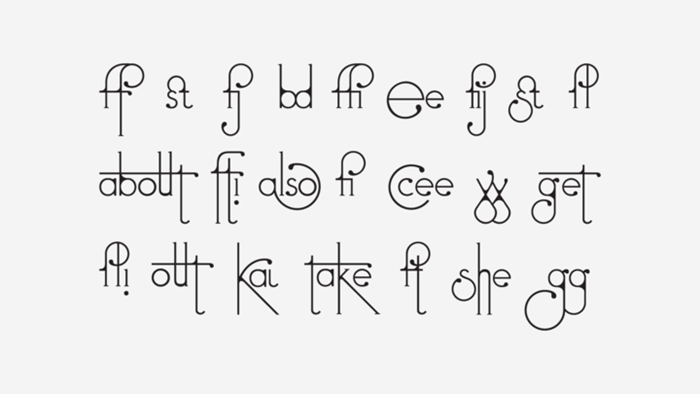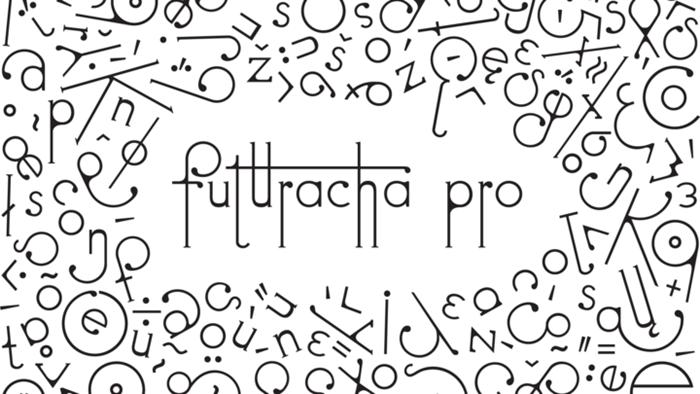
สร้างงานดีไซน์ให้ล้ำได้อีก!! ด้วยฟอนต์แปลงร่าง “Futuracha Pro” ที่ได้รับแรงบันดาลใจมาจากแมลงสาบ
เบื่อกับการใช้ฟอนต์ เรียบ ๆ เดิม ๆ กับงานออกแบบของคุณกันบ้างไหมครับ ? วันนี้ผมมีฟอนต์เจ๋ง ๆ มาแนะนำกัน รับรองว่าฟอนต์นี้จะทำให้ท่านต้องตะลึงเพราะว่ามันสามารถเปลี่ยนรูปร่างของตัวเองได้ตามการใช้งานของเรา ถ้าพร้อมแล้ว ไปรู้จักกับ ฟอนต์ “Futuracha Pro” กันเลยครับ
ความพิเศษของฟอนต์ Futuracha Pro นี้คือมันสามารถปรับและเปลี่ยนรูปแบบของตัวอักษรได้ด้วยตัวของมันเอง ซึ่งการเปลี่ยนรูปแบบของมันนั้น จะเปลี่ยนไปตามรูปแบบคำ รูปแบบประโยคที่คุณพิมพ์ครับ
โดยเจ้าฟอนต์ที่เปลี่ยนร่างได้เรื่อย ๆ นี้ เป็นผลงานการออกแบบโดยกราฟิกดีไซน์เนอร์นามว่า Odysseas Galinos Paparounis จากแบรนด์ดิ้งเอเจนซี่ høly ในประเทศกรีก โดยเจ้าฟอนต์นี้เป็นรุ่นพัฒนาของฟอนต์ Futuracha ที่ได้รับการยกย่องว่าเป็นหนึ่งในฟอนต์ที่ยอดเยี่ยมที่สุดของปี 2012
ที่มาของแรงบันดาลใจในการออกแบบฟอนต์นี้ก็เป็นอะไรที่น่าเหลือเชื่อไม่แพ้ตัวฟอนต์เลยทีเดียวนะครับ เพราะคุณ Paparounis ผู้ออกแบบนั้นเขาได้บอกว่า ได้รับแรงบันดาลใจในการออกแบบฟอนต์จากหนวดและหนามตรงขาของ“แมลงสาบแคริเบียน(Caribean Cockroach) ” อีกทั้งชื่อ Futuracha นั้น ก็มาจากคำว่า “Futura” ผสมผสานกับคำว่า “Cucaracha” ซึ่งแปลว่าแมลงสาบในภาษาสเปน นั่นเอง